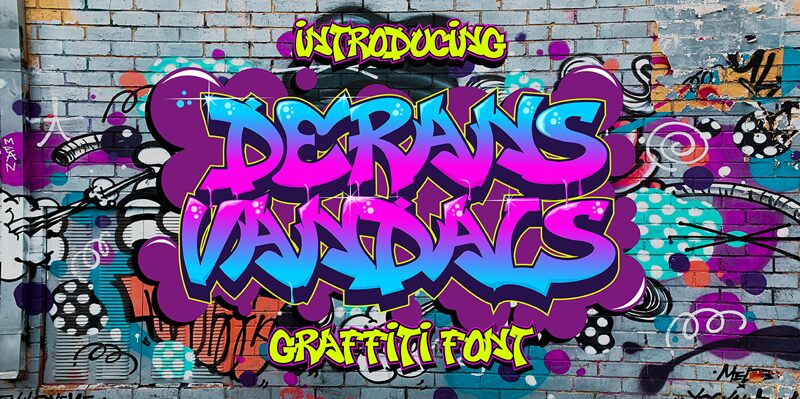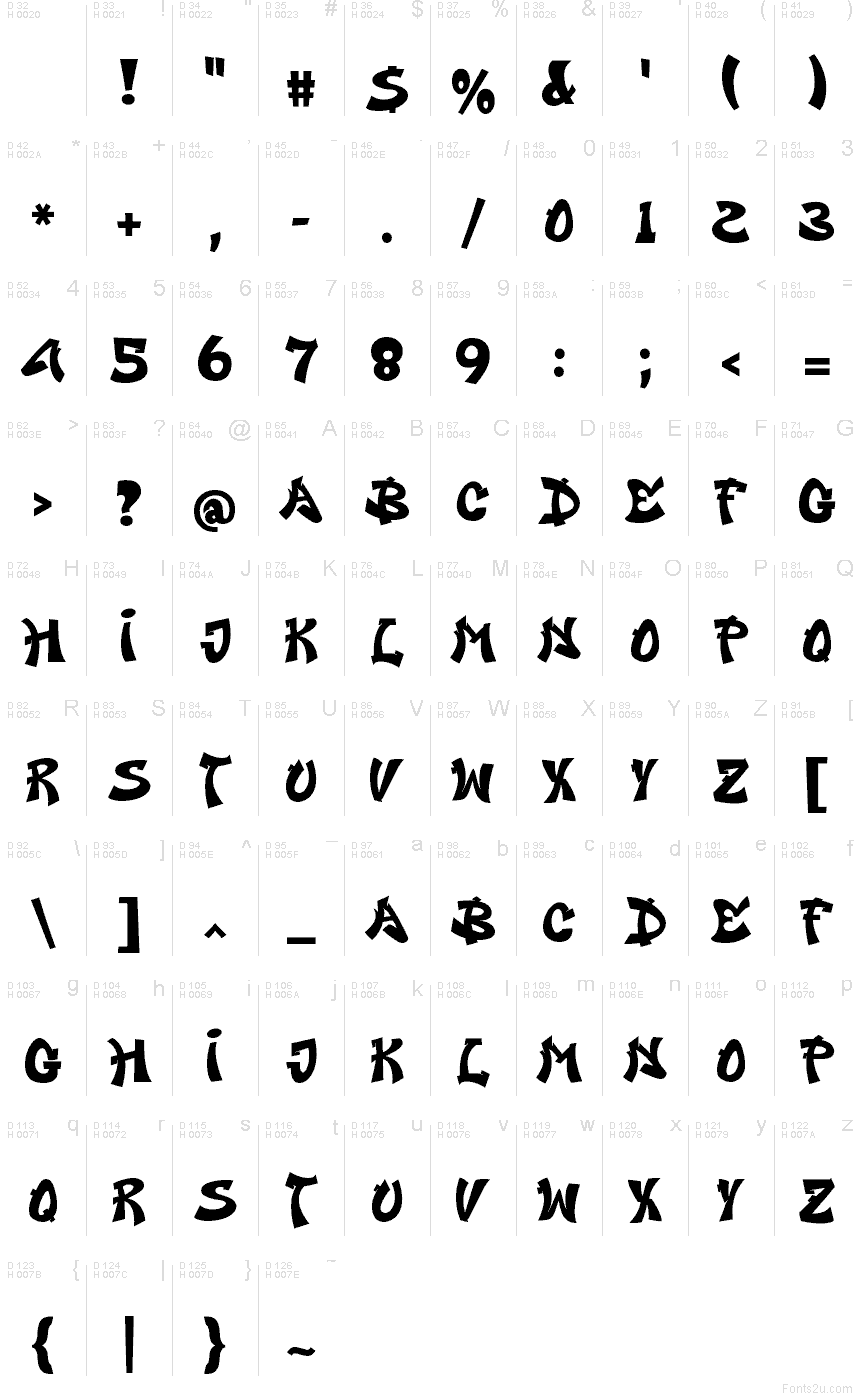
Derans Vandals od Cikareotype je bezplatné graffiti písmo se švihovými, propojenými písmeny a ostrými úhlovými řezy, které slovu dodávají vzhled ručně kreslené streetové tvorby. Tvary kombinují zaoblené křivky s ostrými zlomy, takže působí jako sprejerské, improvizované písmo namísto tuhého a formálního fontu.
Derans Vandals skvěle funguje na graffiti plakátech, hudebních obalech, streetwearové grafice, letácích na akce, logotypech a výrazných nadpisech na sociálních sítích, protože jeho nerovnoměrný rytmus a vyřezávané hrany dodávají krátkým textům syrový městský nádech. Tento bezplatný font se také hodí pro vlastní lettering, grafiku ve stylu tagů a plakátové akcenty, kde lze tvary využít ve velké velikosti s dostatečným rozestupem, aby vynikly jejich ostré hrany.